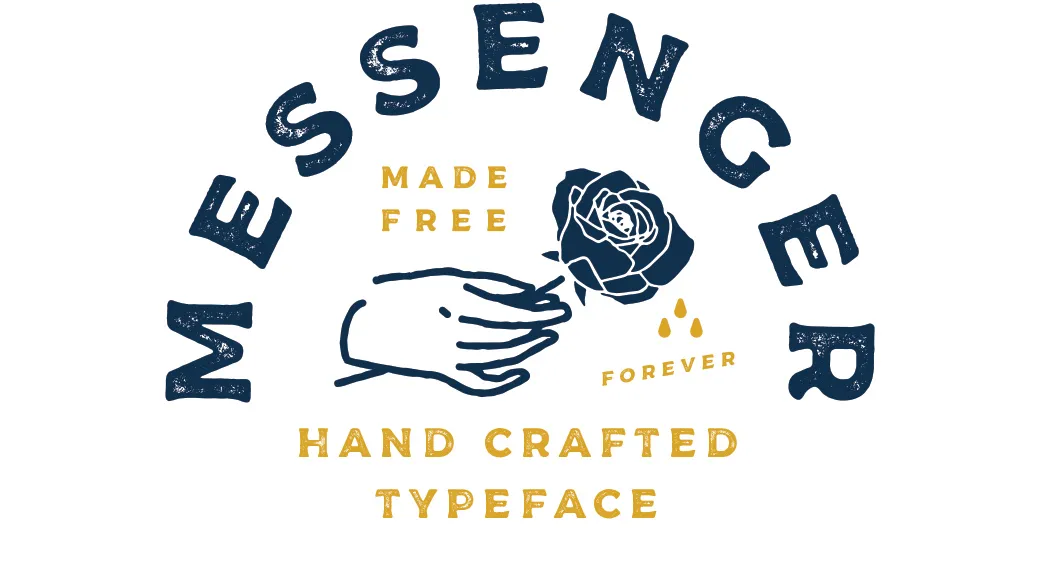
Messenger Typeface é uma fonte serif cuidadosamente feita pelo designer Alex Joganic. Inspirada no design vintage, essa fonte vem em três estilos e pode ser usada para projetos comerciais e pessoais. Suavemente adaptável a diversas necessidades de gráficos, ela se destaca especialmente para o design de mídia social, impressão, logotipos, panfletos, camisetas e embalagens. Seu uso é perfeitamente adequado para qualquer tipo de criação gráfica. Com suas linhas elegantes e detalhes bem feitos, Messenger oferece uma fonte serif que é tanto um ativo incrível como uma ferramenta versátil para designers gráficos de todo o Brasil.